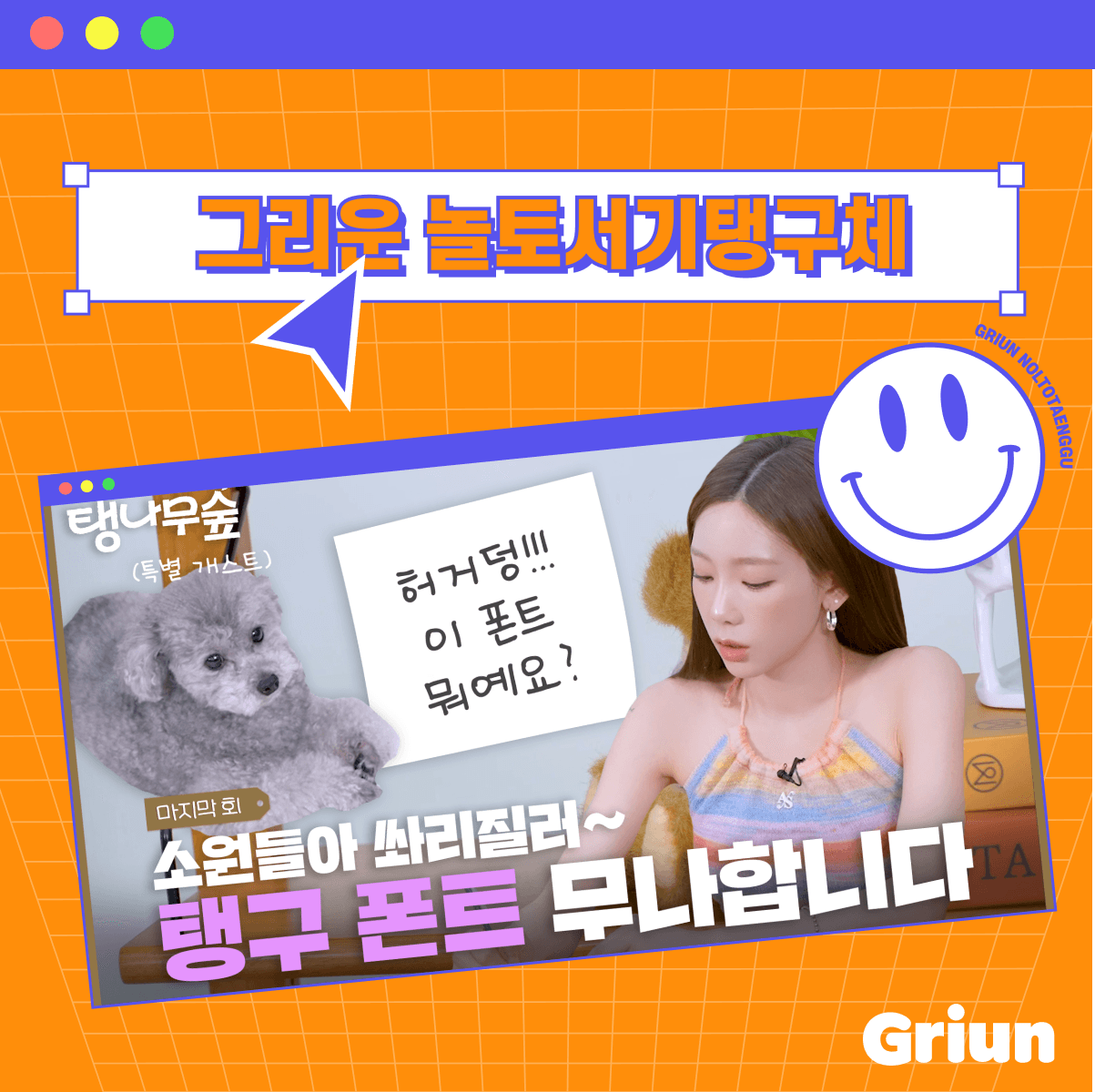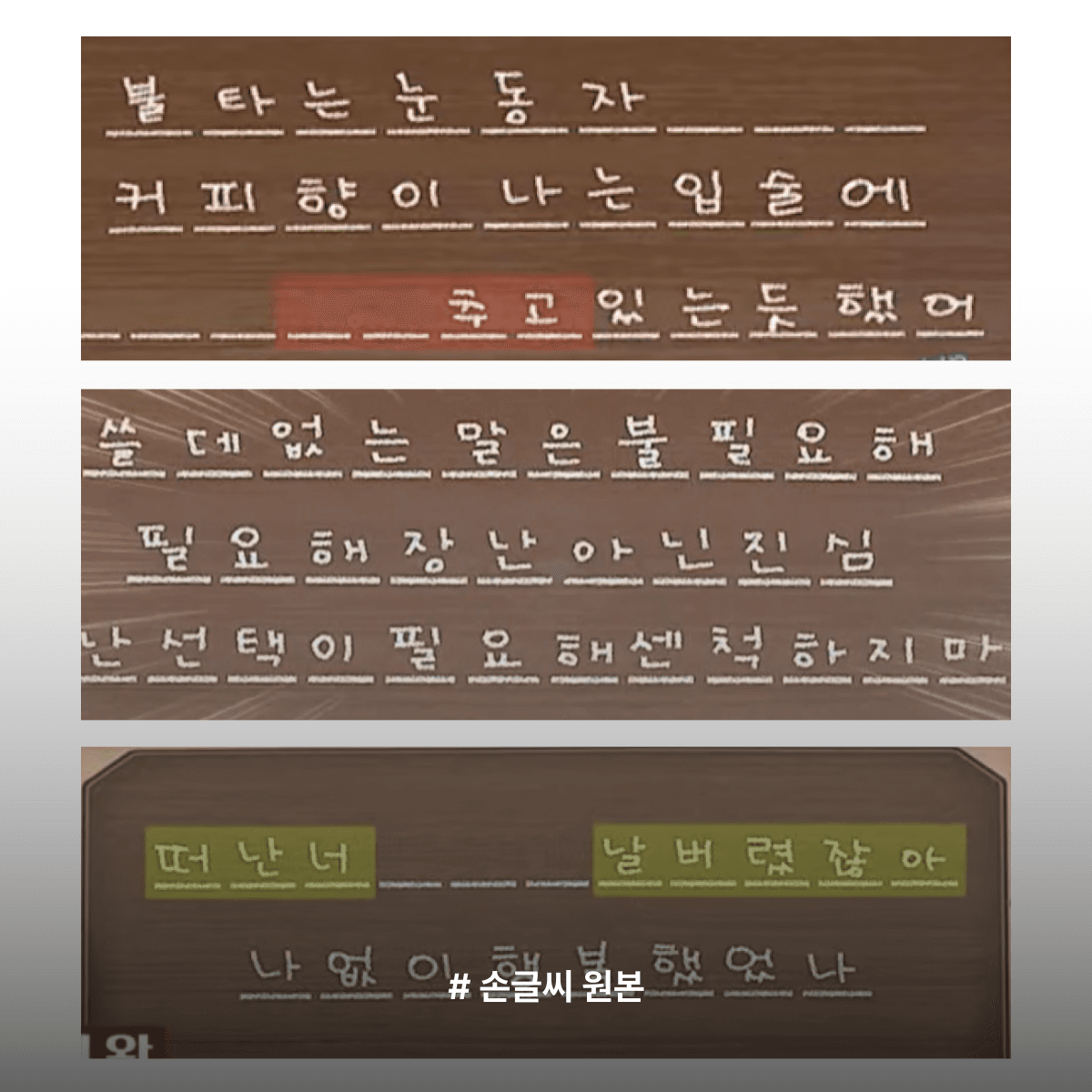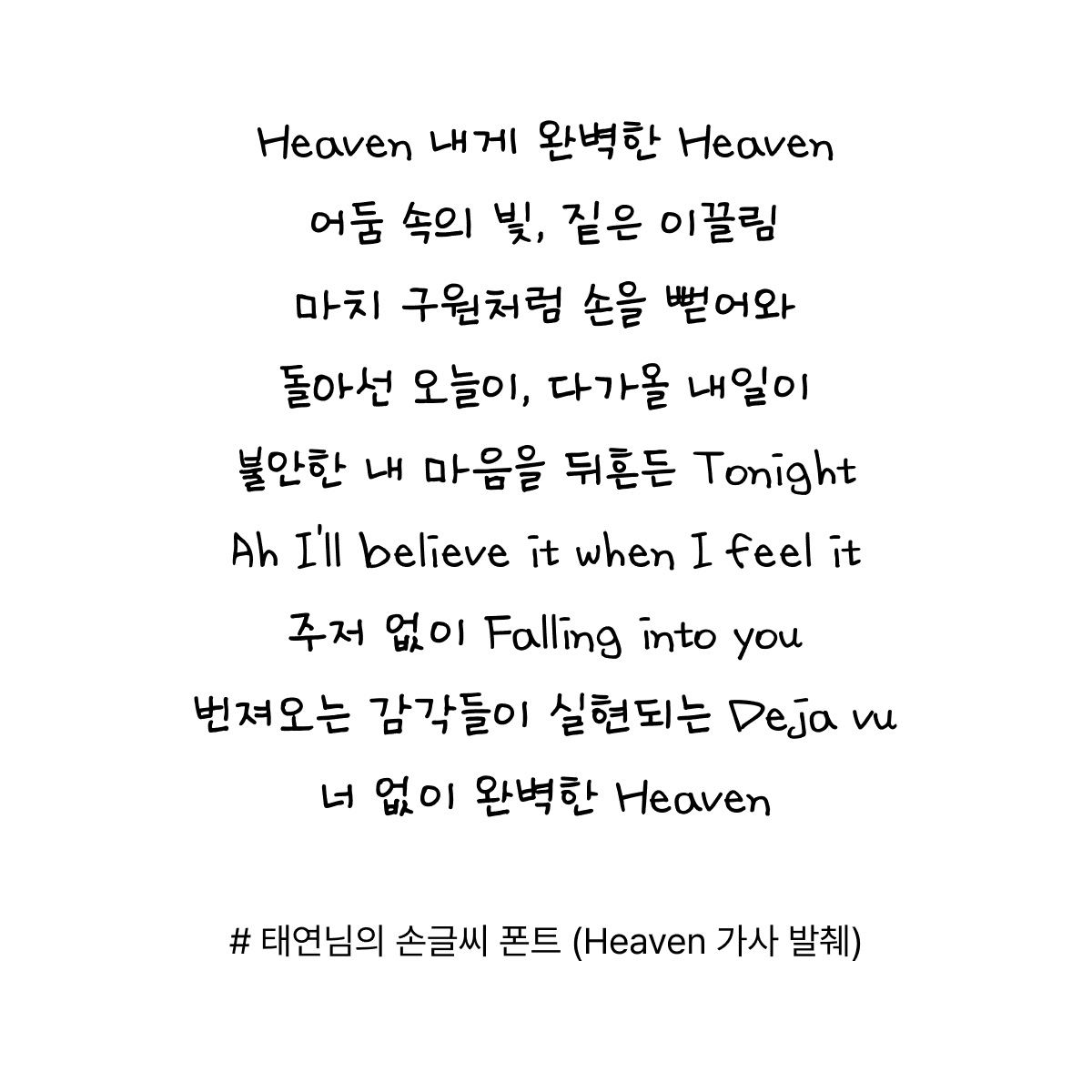
그리운 놀토서기탱구체
Griun NoltoTaenggu
그리운 놀토서기탱구체 소개
'그리운 놀토서기탱구체'는 SM Entertainment와 그리운(Griun)이 공동 제작한 폰트입니다. 시장 속 핫한 음식을 걸고 노래 가사 받아쓰기 게임을 하는 음악 예능 '놀라운 토요일'의 서기인 태연님은 또박또박 앙증맞은 손글씨를 가지고 있는데요. 팬분들의 열화와 같은 요청으로 태연님의 손글씨 폰트를 만들게되었답니다. 태연님이 직접 소개하고 이름도 지어주었다능~ 그 내용이 궁금하다면 유튜브 탱나무숲을 확인해주세요! 태연님의 귀여운 폰트를 쓰면서 우리 함께 새로운 탱나무숲을 기다려보자구요! >_<!!